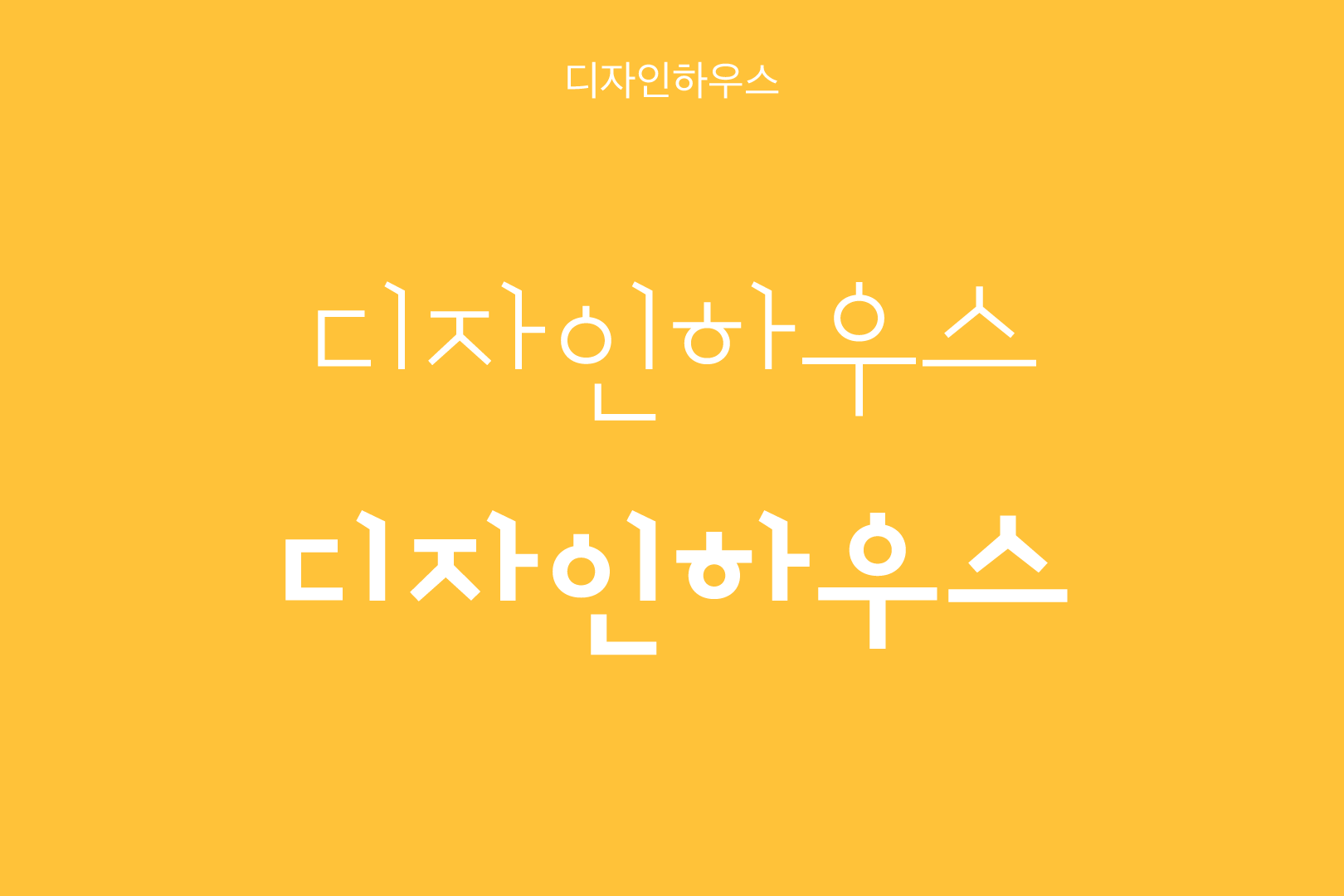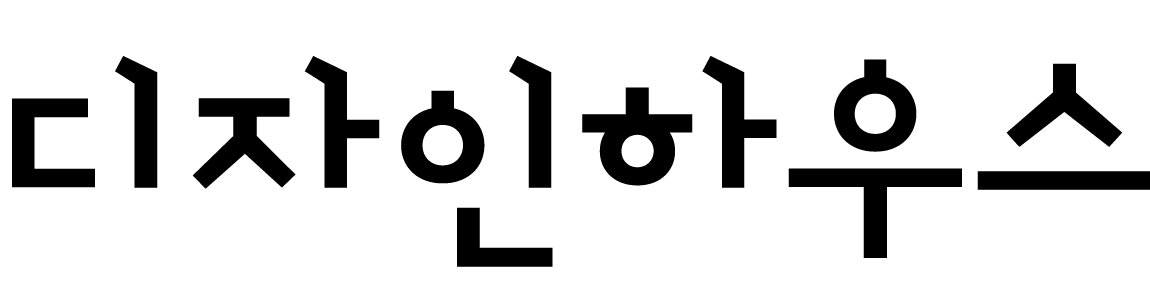
디자인하우스
월간 <디자인> 전용폰트로서 디자인하우스에서 발행하는 다양한 간행물에 모두 사용할 수 있도록 개성이 강하기보다는 중립적인 폰트로 디자인했다. 탈네모꼴을 통해 리드미컬한 이미지를 표현했고 외래어 표기가 많은 잡지의 특성을 고려해 R과 L, B와 V, P와 F를 구분할 수 있는 새로운 표기 글자를 제작했다.
- 2종
- 2016